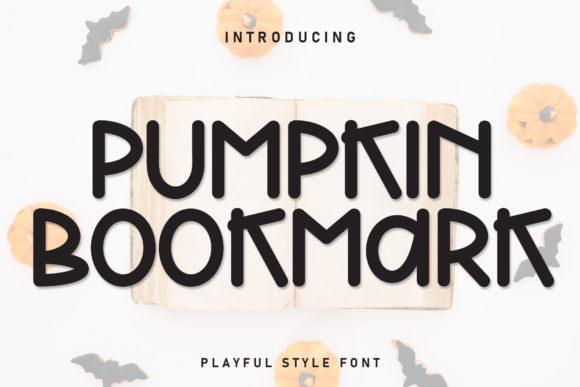
Pumpkin Bookmark
適切なデザイン要素を見つけるのは難しい場合がありますが、Pumpkin Bookmarkは作品を即座に引き立てる優れたコレクションを提供します。
POD(オンデマンド印刷)製品、結婚式の招待状、またはソーシャルメディアのグラフィックを作成している場合でも、Pumpkin Bookmarkは理想的です。